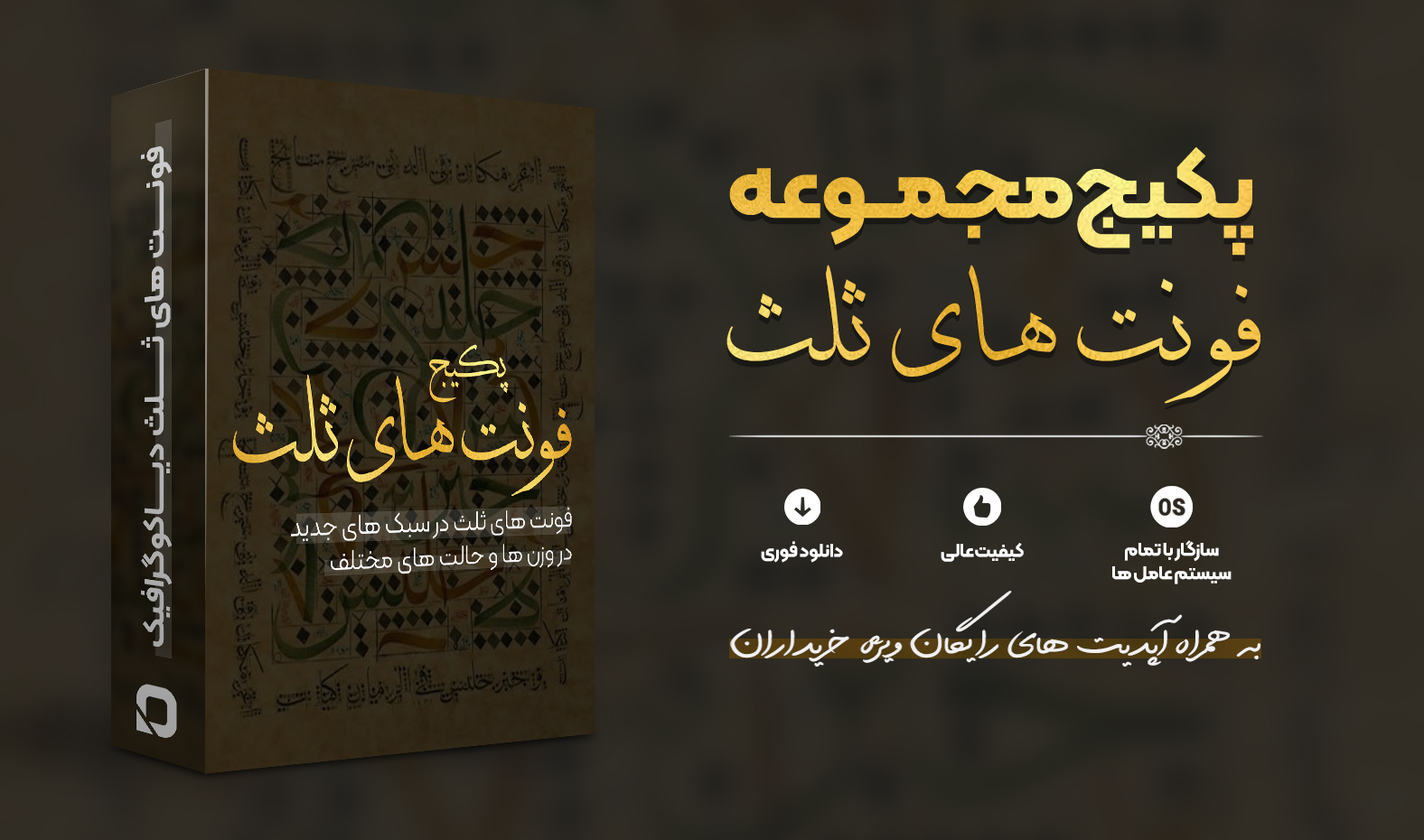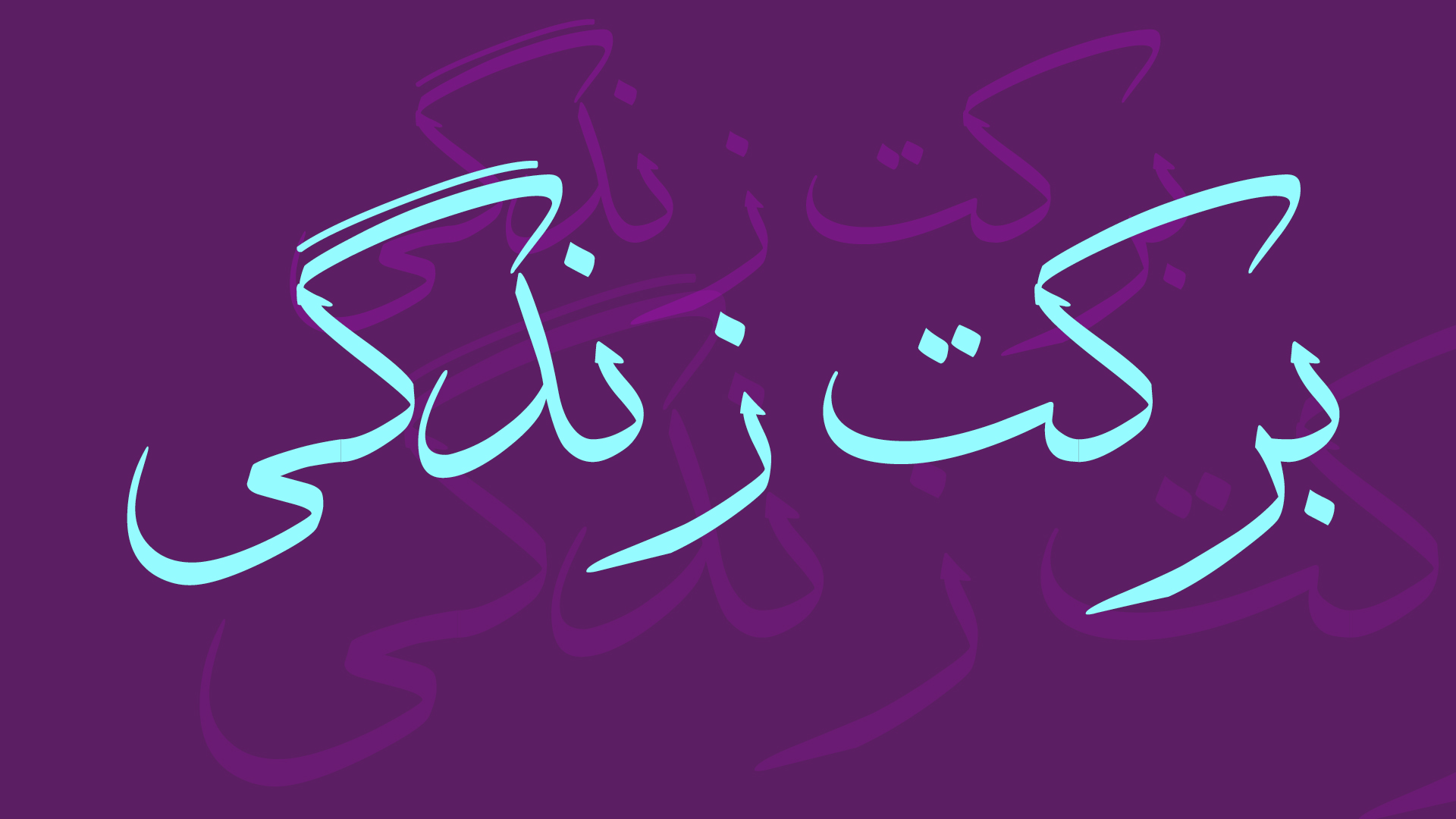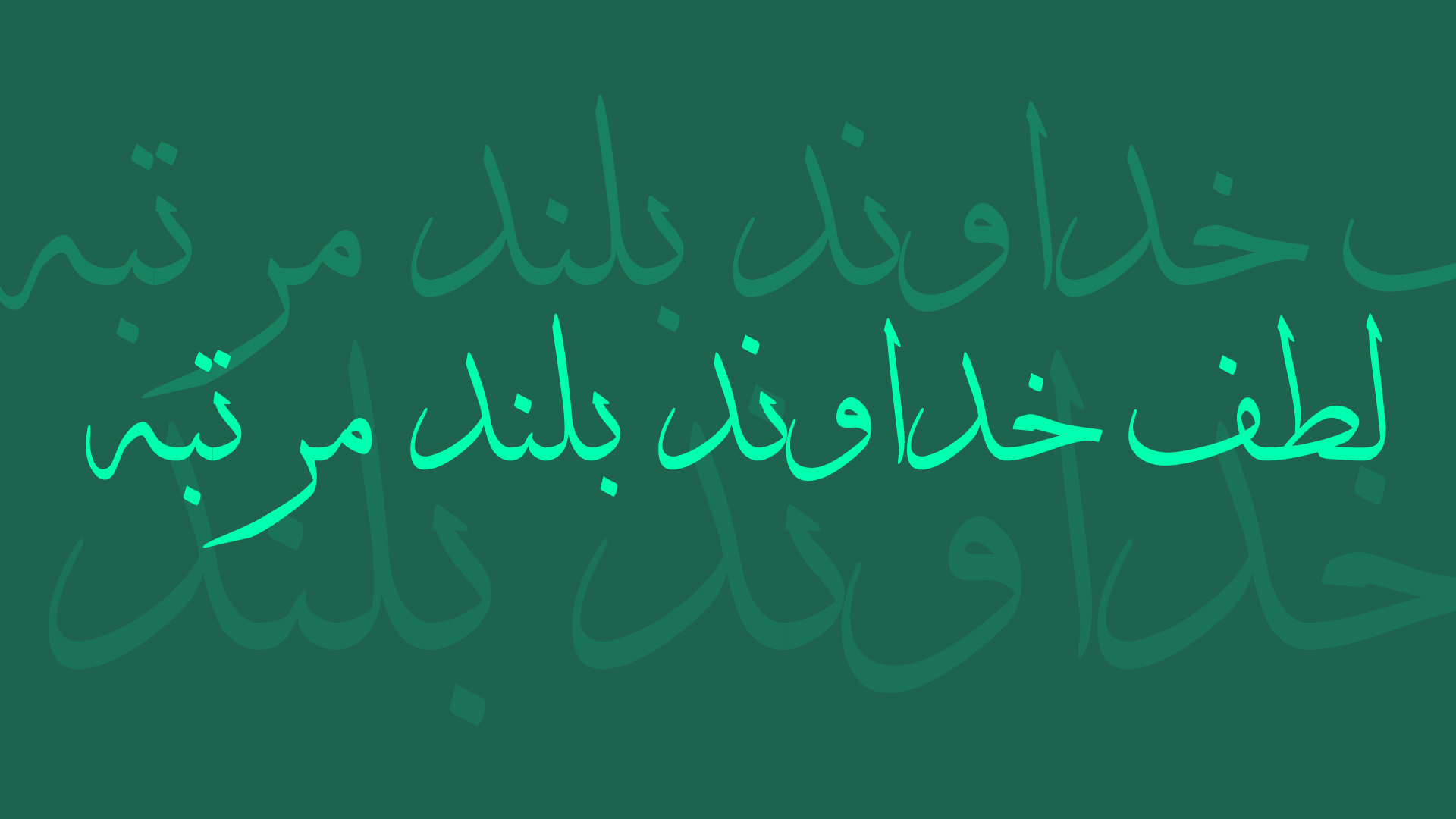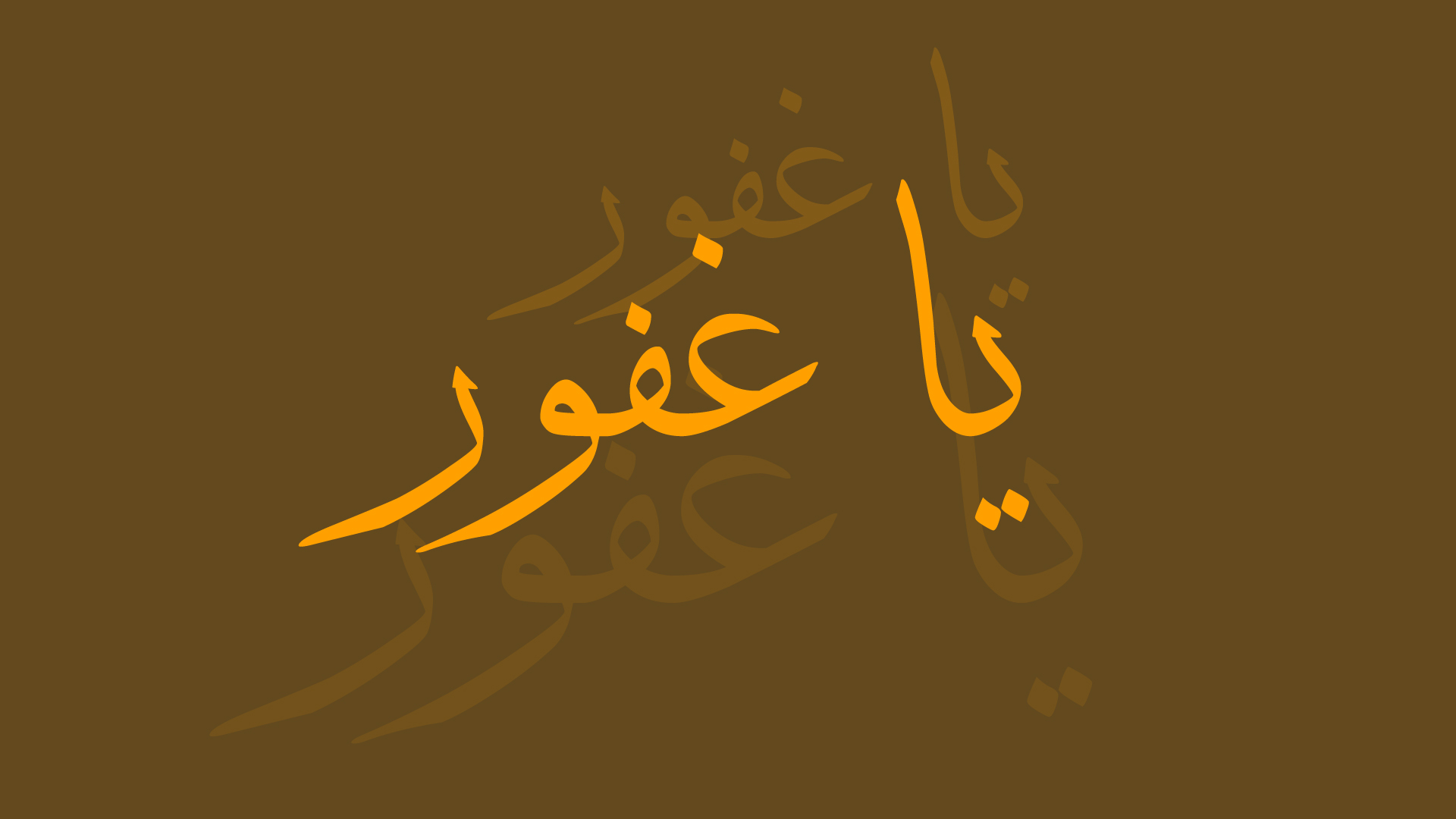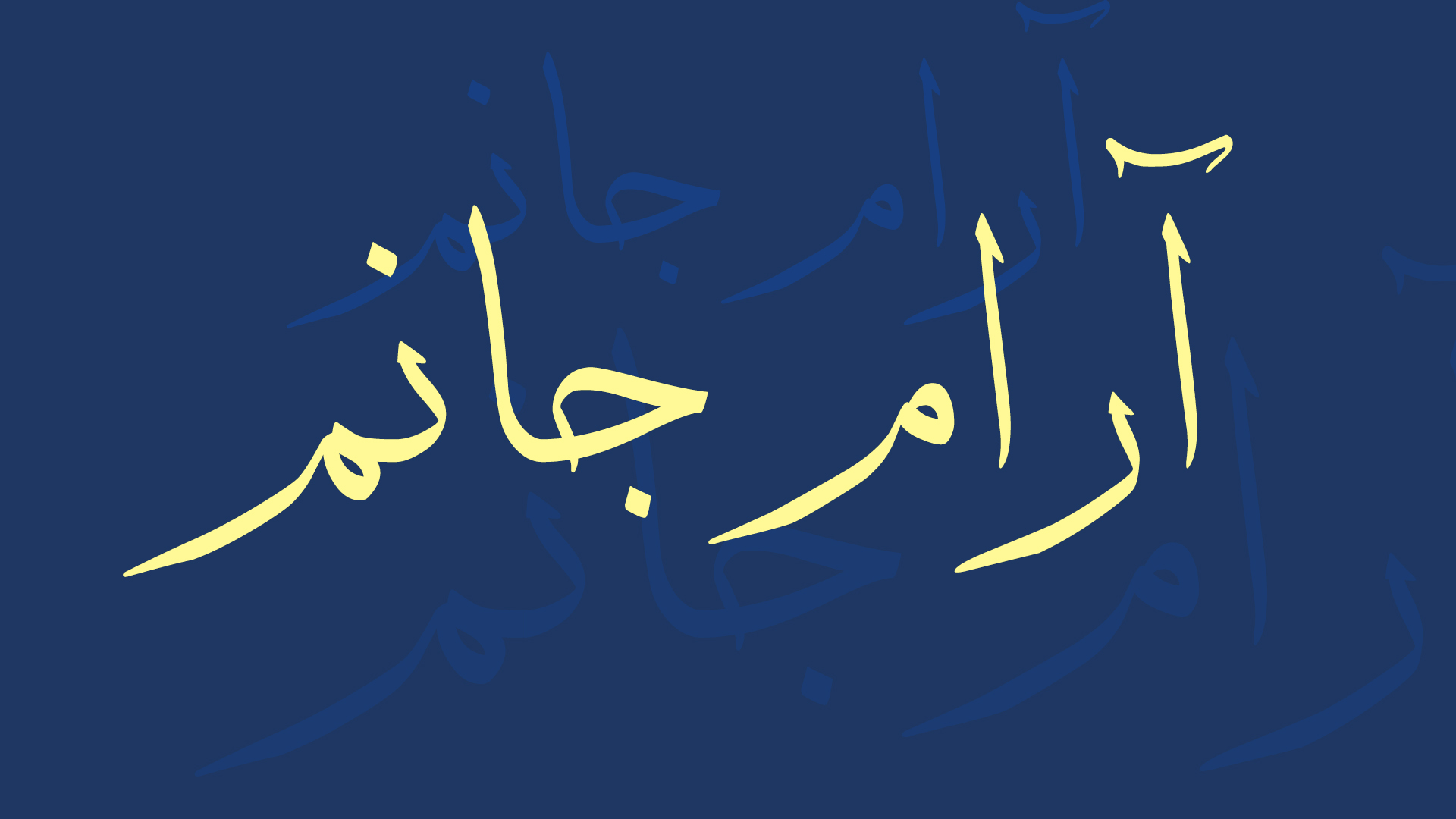
۱۴ فونت حرفهای ثلث با کیفیت بالا، مناسب طراحی آثار مذهبی، قرآنی، فرهنگی و هنری، در یک پکیج کامل و آماده استفاده.
اگر به دنبال فونتهایی هستید که شکوه هنر اسلامی را در طراحیهای شما به نمایش بگذارند، پکیج فونتهای ثلث دیاکوگرافیک انتخابی ایدهآل است. این مجموعه شامل ۱۴ فونت منتخب ثلث است که برای طراحی پوسترهای مذهبی، آیات قرآن، احادیث، کتیبهها، بنرهای مناسبتی، تابلوهای هنری و آثار فرهنگی گردآوری شدهاند.
فونت ثلث یکی از باشکوهترین و اصیلترین خطوط خوشنویسی اسلامی است که قرنها در کتابت قرآن، معماری اسلامی، کتیبههای تاریخی و آثار هنری مورد استفاده قرار گرفته است. اکنون میتوانید این زیبایی را تنها با چند کلیک در پروژههای گرافیکی خود به کار بگیرید.
پیدا کردن فونتهای ثلث باکیفیت و استاندارد همیشه کار سادهای نیست. بسیاری از فونتهای موجود ناقص، قدیمی یا فاقد کیفیت لازم برای طراحی حرفهای هستند.در این مجموعه، بهترین فونتهای ثلث انتخاب شدهاند تا بدون نیاز به جستجوی طولانی، همیشه مجموعهای کامل و کاربردی در اختیار داشته باشید.
پکیج فونتهای ثلث دیاکوگرافیک مجموعهای کوچک اما ارزشمند از زیباترین فونتهای ثلث است که با دقت انتخاب شدهاند تا نیاز طراحان حرفهای و علاقهمندان به هنر خوشنویسی اسلامی را برطرف کنند. اگر به دنبال خلق آثاری با هویت اصیل، باشکوه و ماندگار هستید، این مجموعه میتواند یکی از کاربردیترین ابزارهای طراحی شما باشد.
این مجموعه با تمرکز بر کیفیت و کاربرد، گلچینی از بهترین فونتهای ثلث را در اختیار شما قرار میدهد تا بدون اتلاف وقت، طراحیهای مذهبی و هنری خود را با جلوهای اصیل و حرفهای آغاز کنید.